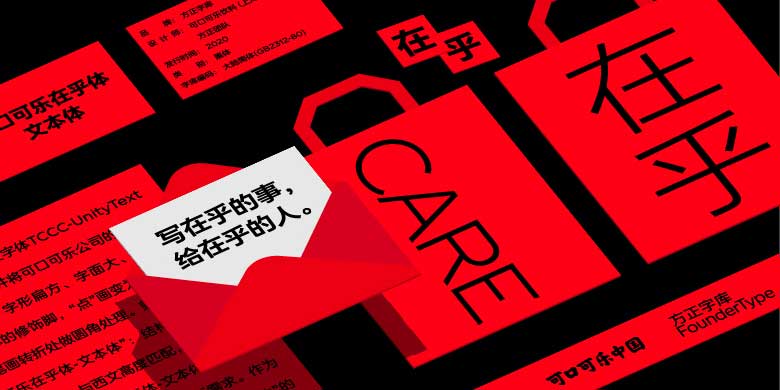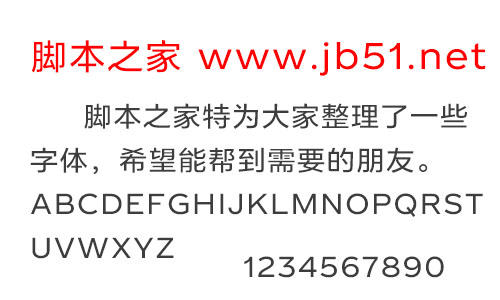
可口可乐在乎体-文本体以可口可乐现有西文字体TCCC-UnityText的设计特点为风格依据,并将可口可乐公司的品牌特色融入到笔画设计中,字形扁方、字面大、中宫宽博,去除了传统黑体的修饰脚,“点”画变为“竖点”并增加了8°切角,笔画转折处做圆角处理……兼具这些设计特征的“可口可乐在乎体-文本体”:结构严谨,线条刚柔并济,简约现代,与西文高度匹配,并且阅读舒适、识别性强。
“可口可乐在乎体-文本体”包含5个字重,可以满足从标题到正文的不同排版需求。作为“可口可乐在乎体”家族的重要组成部分,“文本体”的出现,希望能为大家提供一种既有个性特征又有人情味的字体选择。欢迎喜欢可口可乐在乎体-文本体的朋友前来下载使用。
2020年5月8日,可口可乐134岁生日的这天,可口可乐官方正式对外发布了首套中文定制字体——可口可乐在乎体。可口可乐在乎体由可口可乐、汉字文化推广机构“好字在”、方正字库三方共同打造,它以可口可乐重返中国早期的老商标字体为灵感原点,将中国传统书法的精髓与现代审美相结合,并将水的形态与精神融入到了设计之中,充分表达了中国人对“在乎”的理解和诠释,也体现了可口可乐中国的企业价值观。
在可口可乐在乎体(楷体风格)的定制合作期间,方正字库也受邀为可口可乐设计了一套适用于文本排版的中文字体,该字体命名为“可口可乐在乎体-文本体”。